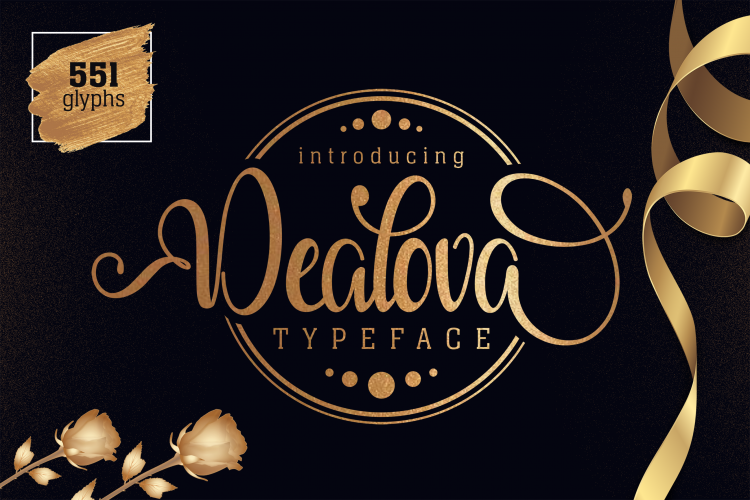
Dealova Script Font – Download Grátis
Descubra a magia do Dealova Script Font, uma elegante fonte de script romântica projetada para abençoar sua próxima jornada diária com beleza e sofisticação. Introduzida pelo designer afredo.fk, essa fonte é um novo lançamento, misturando elementos modernos com a delicadeza da escrita à mão. Com caracteres decorativos e uma linha base que dança ao longo do papel, o Dealova Script Font se destaca em invitações de festa, materiais de marca, cartões de negócio, citações, painéis publicitários, logotipos e muito mais. Perfeita para aqueles projetos que exigem um toque único e sofisticado, essa fonte é uma escolha ótima para quem busca incorporar uma pitada de romance à sua tipografia.